Juegos para despertar vocaciones tipográficas
La vieja máxima «enseñar deleitando» se apoya en la sólida base que sostiene que se aprende mejor y más profundamente cuanto más amena, incluso divertida, sea la forma de transmitir la materia. Una sonrisa relaja, elimina el estrés, y eso ya es ingrediente fundamental para abonar el campo del aprendizaje. Los niños aprenden jugando; el juego es su modo de relacionarse y entrar en contacto con el nuevo mundo al que acaban de llegar. ¿Y por qué no mantener esta idea a lo largo de toda la vida? No hay nada que impida a una persona adulta a seguir disfrutando de lo lúdico y aprovecharse de sus innumerables beneficios.
Tipografía lúdica
La tipografía es una disciplina compleja, que requiere de una gran cantidad de conocimientos técnicos que abarcan campos muy diversos. Mucha gente se siente intimidada a la hora de acercarse al mundo tipográfico, al que suele considerarse poco menos que inaccesible, pero que sea difícil llegar a dominarlo, no quiere decir que no sea enormemente gratificante y que no pueda hallarse en sus procesos de aprendizaje un buen montón de puntos de encuentro con lo lúdico. Acercarse a la tipografía desde cierta perspectiva lúdica, desenfadada incluso, como niños que se dejan llevar por su natural curiosidad, puede convertirse en una experiencia verdaderamente gratificante y quién sabe si el inicio de una relación con las letras más duradera, profundo y fructífera.
Os traigo varias propuestas, diversos y variados juegos alrededor de la tipografía, para que paséis bien entretenidos las mañanas o las tardes o las noches de los findes (o de cualquier otro día de la semana), ahora que casi es mejor no salir de casa. Entretenidos y aprendiendo, que no es poco.
¿Jugamos?
1. Un Tinder para tipografías
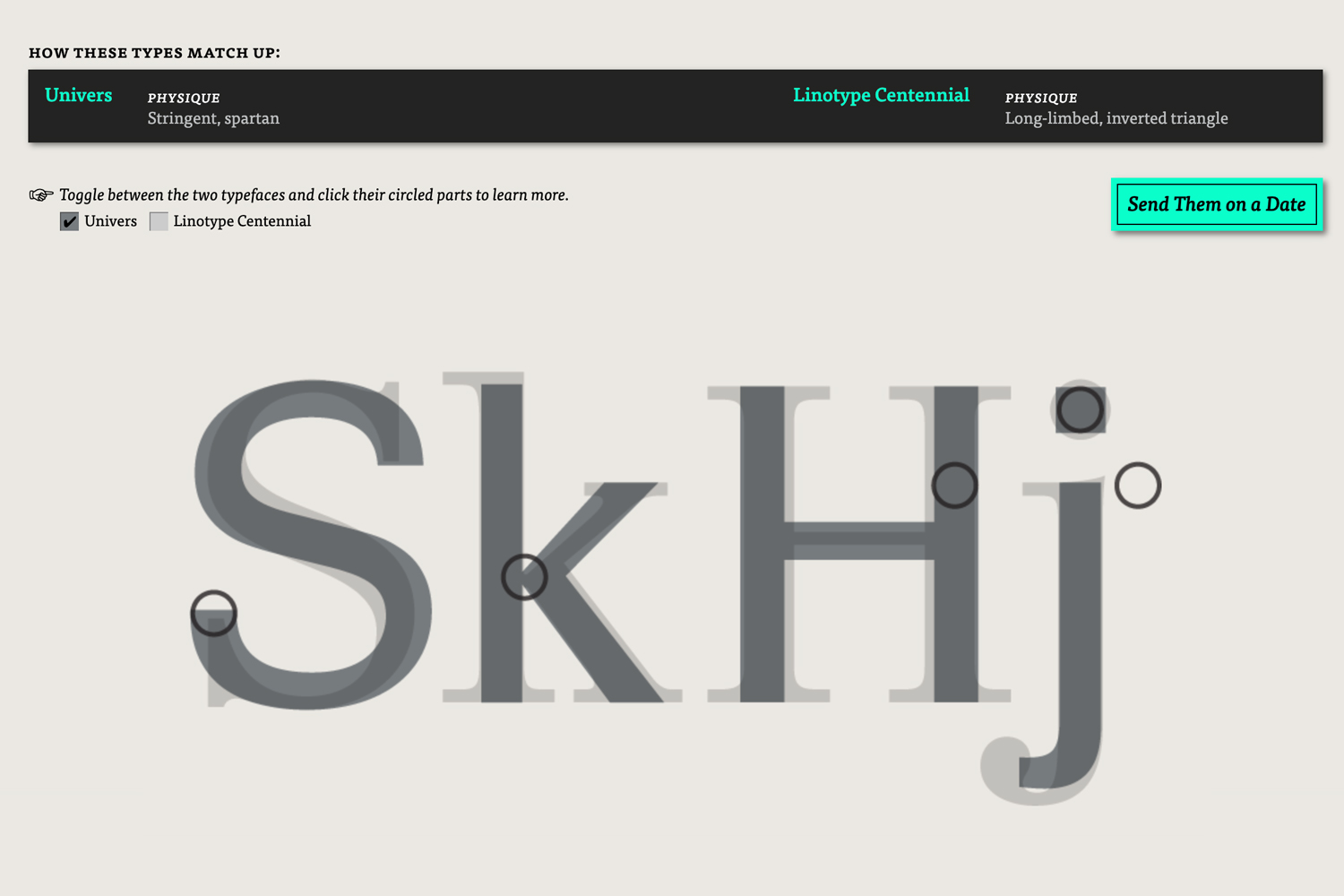
Type Connection es uno de los juegos que te ayuda a aprender a combinar tipografías. El mecanismo, inspirado en webs de cita, es muy ingenioso. Una vez decidida la tipografía que queremos emparejar, podemos escoger el criterio para la elección: la familia, algo similar, algo diferente o explorar el pasado. Elegimos uno de estos cuatro caminos y se nos ofrecen varias opciones tipográficas para combinar con la nuestra. A partir de aquí, obtenemos comparativas muy interesantes; entre ellas, datos históricos de las mismas y opciones de volver atrás si queremos probar otras opciones. Una buenísima opción esta web que ofrece grandes posibilidades de aprendizaje mediante un inteligente y divertido método lúdico. ¡Viva el amor tipográfico!
2. Acierta y vencerás
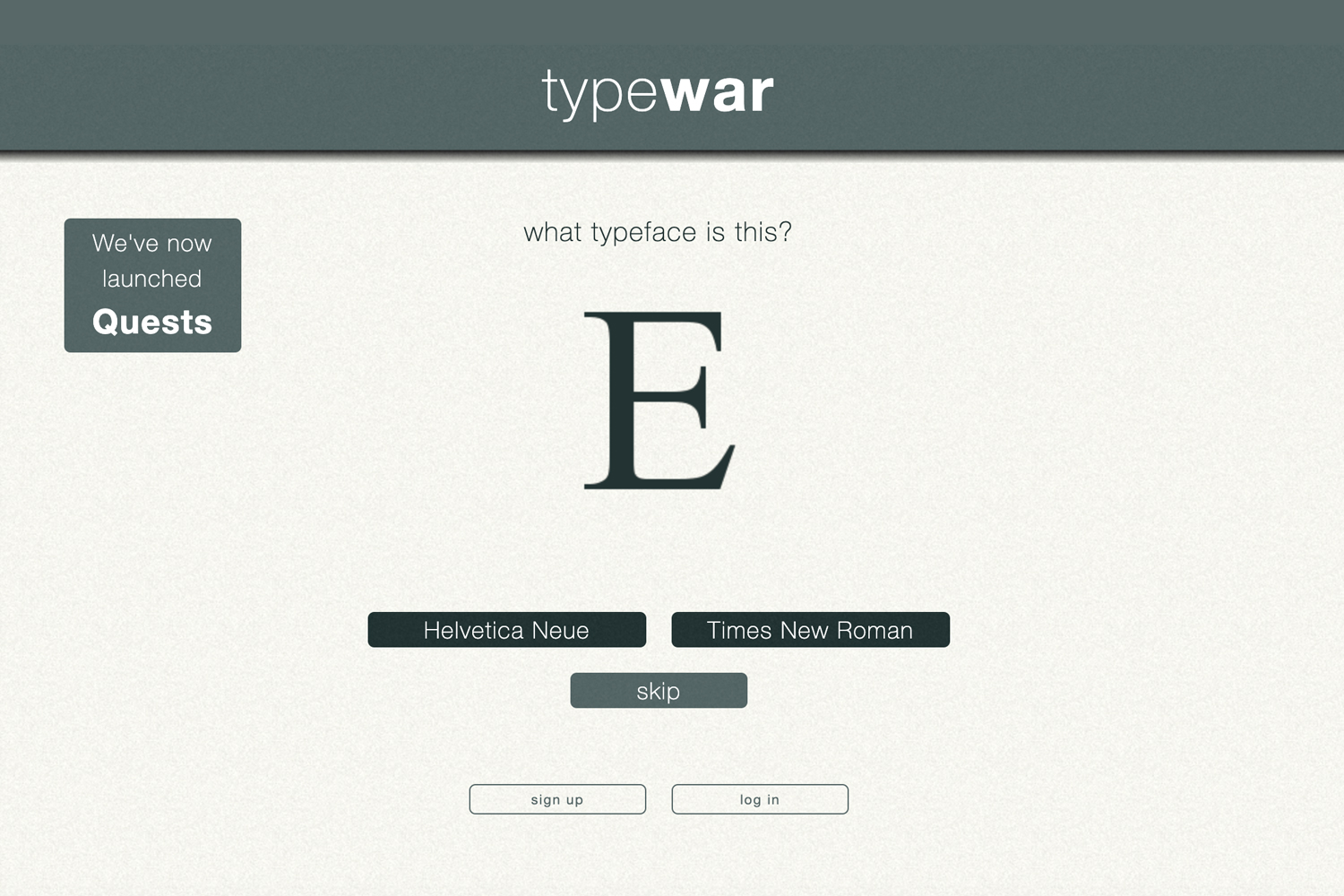
El mecanismo de Typewar es de los que enganchan. Se trata de acertar el tipo de letra entre dos opciones dadas. De este modo, a través de las puntuaciones que obtenemos, vamos avanzando en el juego. La pega es que requiere registro.
3. Dominar el arte del kerning
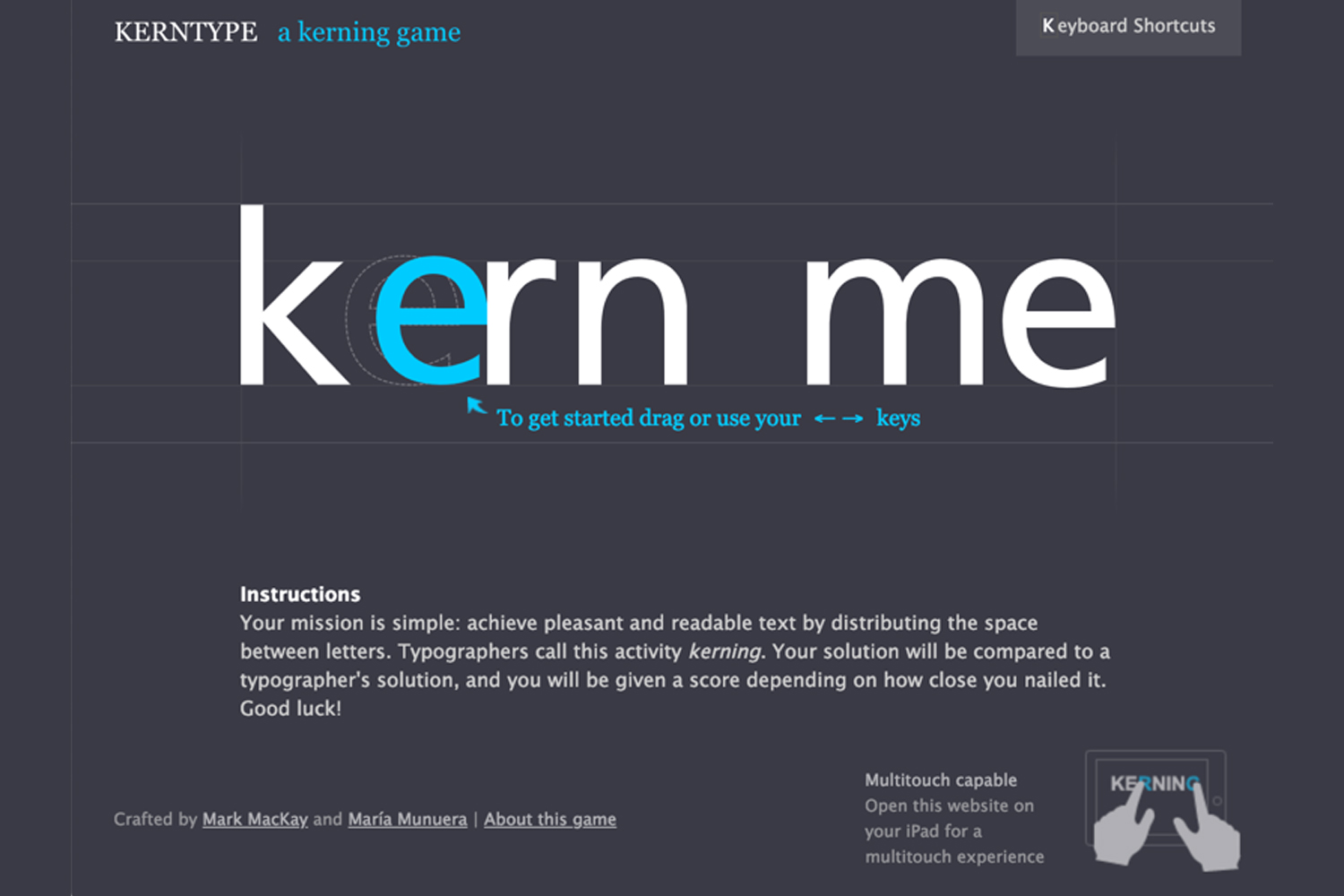
Method of Action es una elegante web con juegos muy bien planteados y desarrollados para practicar algunos rudimentos del diseño gráfico y la tipografía.
Uno de los juegos estrella es KernType, un juego para practicar el espaciado entre pares de letras, afinar la vista y entender que la tipografía y el espaciado tiene mucho que ver con los ajustes ópticos. Además de aprender a espaciar correctamente, lo hacemos con diferentes tipografías con las que nos podemos ir familiarizando.
4. Vienen curvas… de Bézier
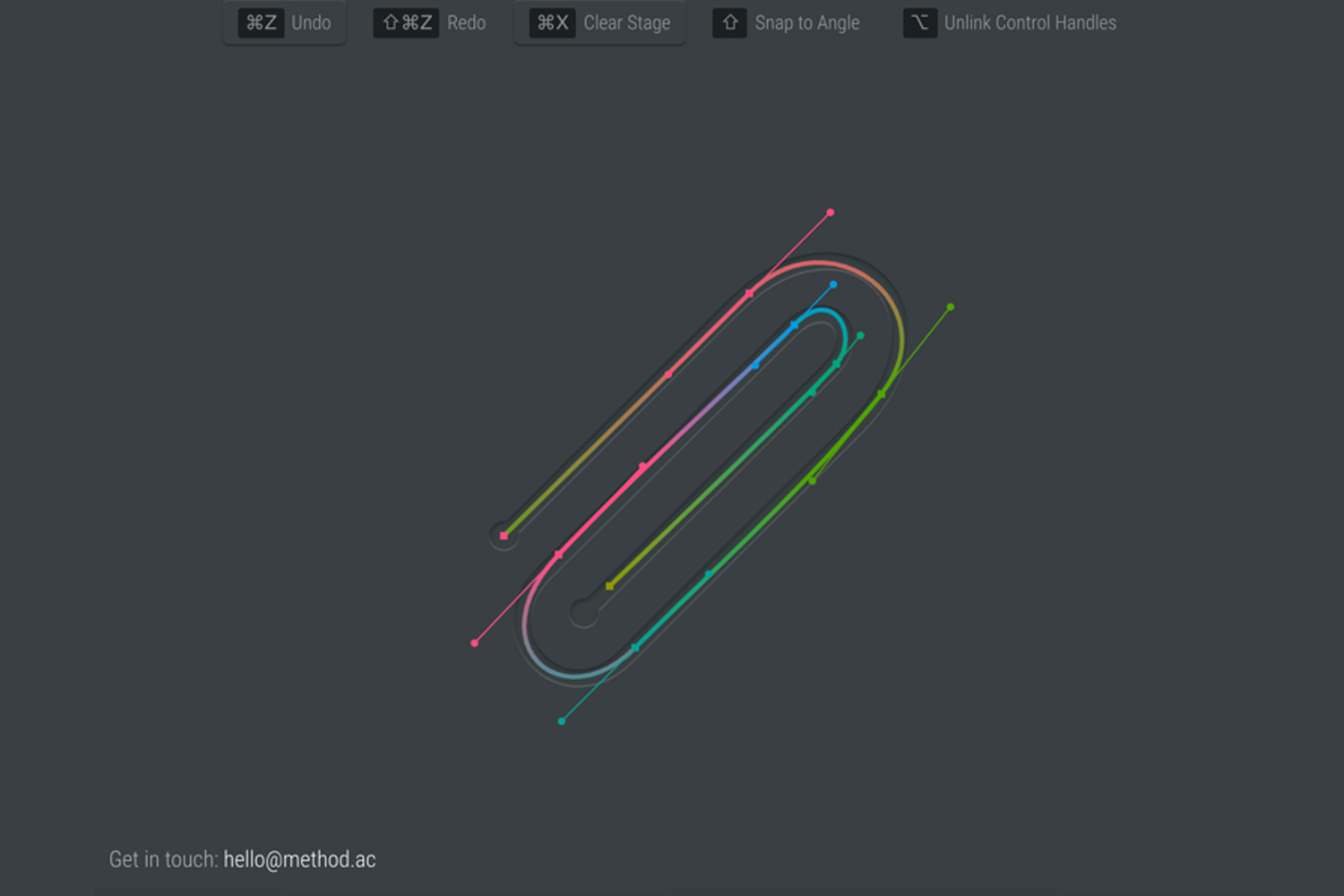
Dentro de Method of Action, también encontramos, The Bézier Game, un juego para iniciarse en el manejo de la famosa herramienta pluma, clave en el diseño vectorial ya sea tu finalidad ilustrar o crear una tipografía. El juego simula de manera simplificada el movimiento de la herramienta, los nodos, manejadores e incluso la «goma elástica» de Illustrator para previsualizar el trazado entre el primer punto de ancla y el puntero del ratón. Un juego de lo más útil.
5. Afina el ojo tipográfico
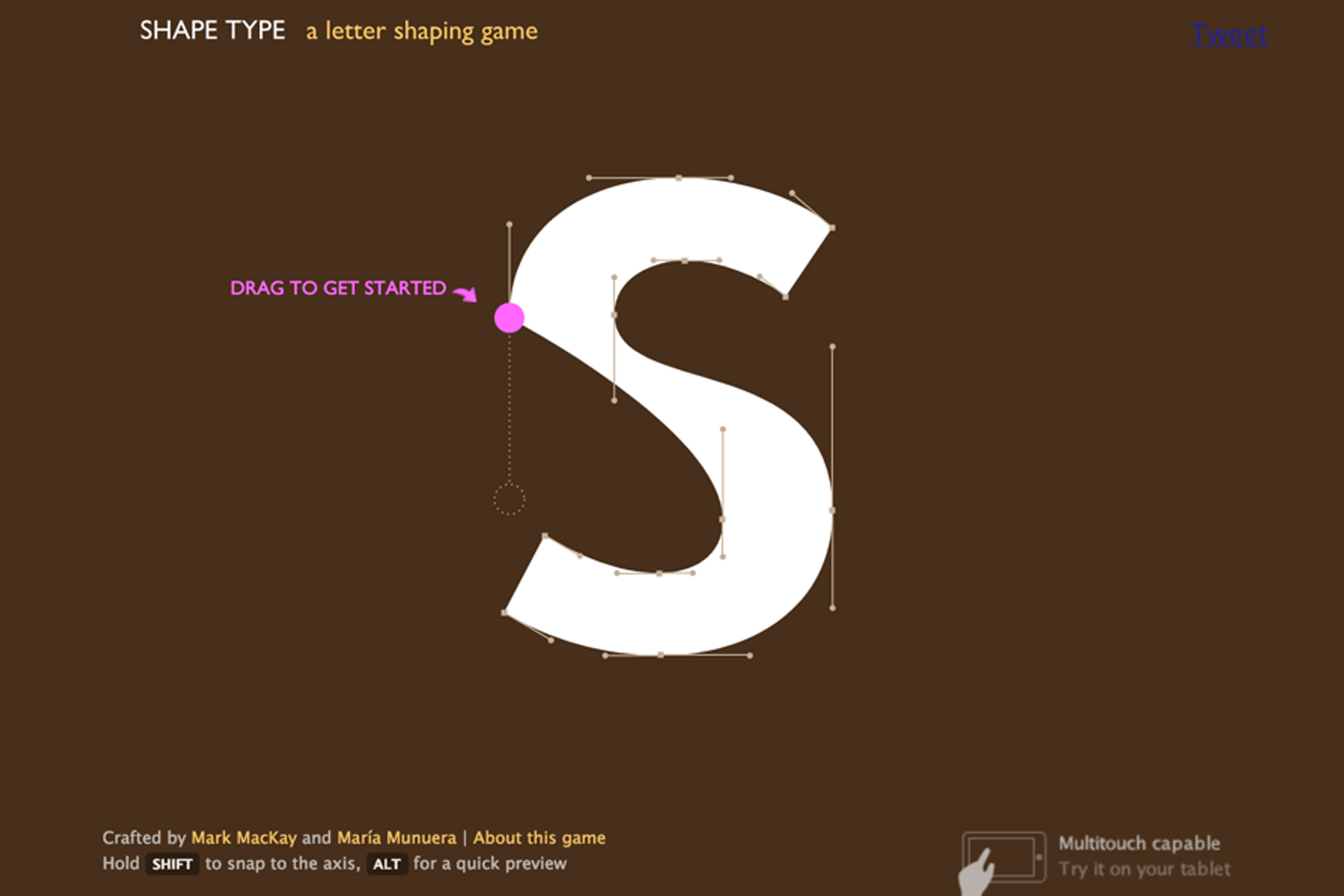
El tercer juego tipográfico de Method of Action es Shape Type, un imprescindible para afinar curvas y con ello perfeccionar las formas de las letras y sus contraformas, que son igual o más importantes. Como podrás comprobar, esta suite es lúdica, muy distraída y con mucho sentido práctico.
6. Encuentra las diferencias, si puedes
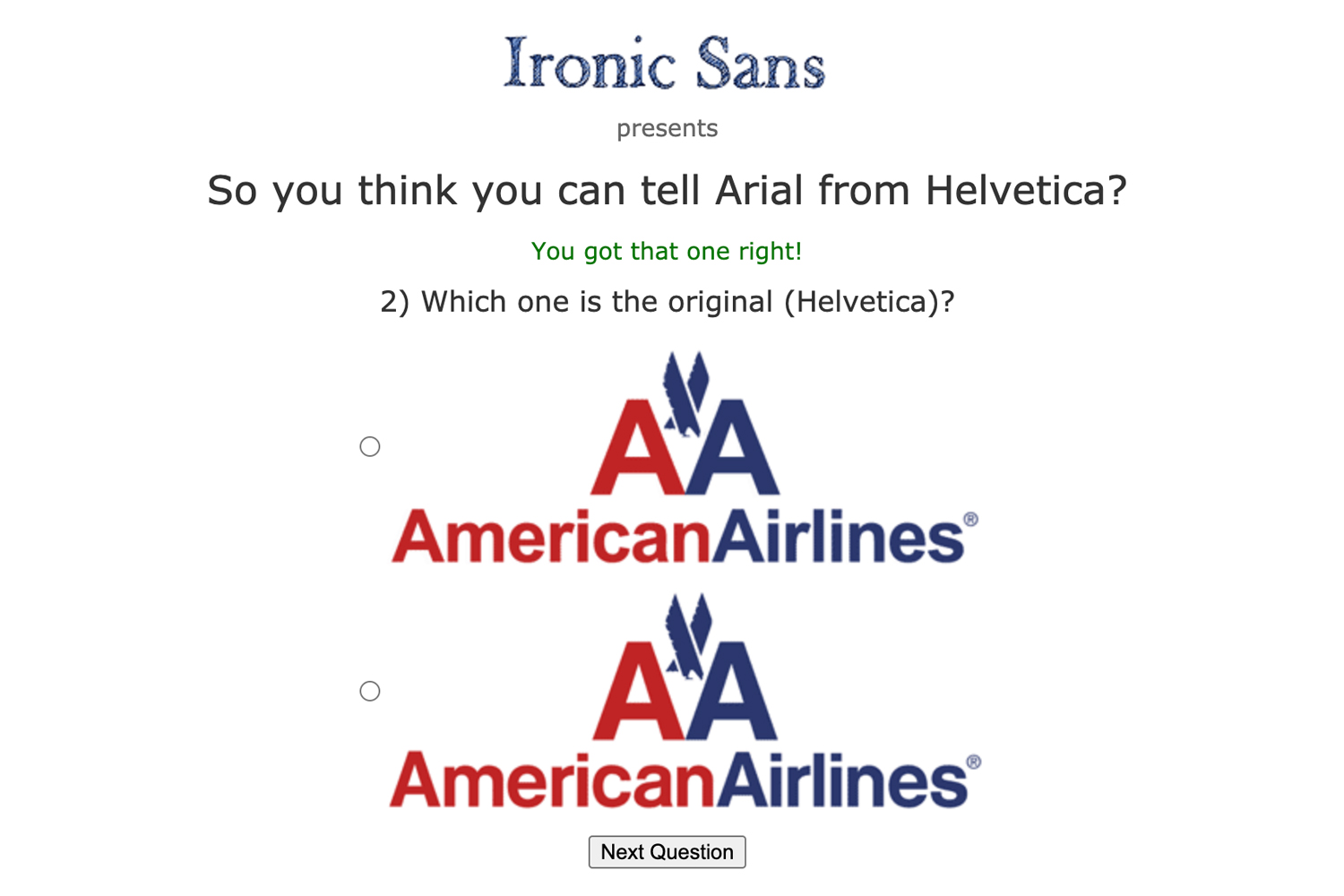
Por último, os proponemos un juego con mucho de esa clase de sentido del humor puñetero y afilado, muy anglosajón. Se trata de Helvarialquiz, donde se plantea la siguiente pregunta: ¿Crees que puedes distinguir entre Arial y Helvetica? Y como podrás comprobar, no es tan fácil distinguirlas.
7. Apunta y dispara
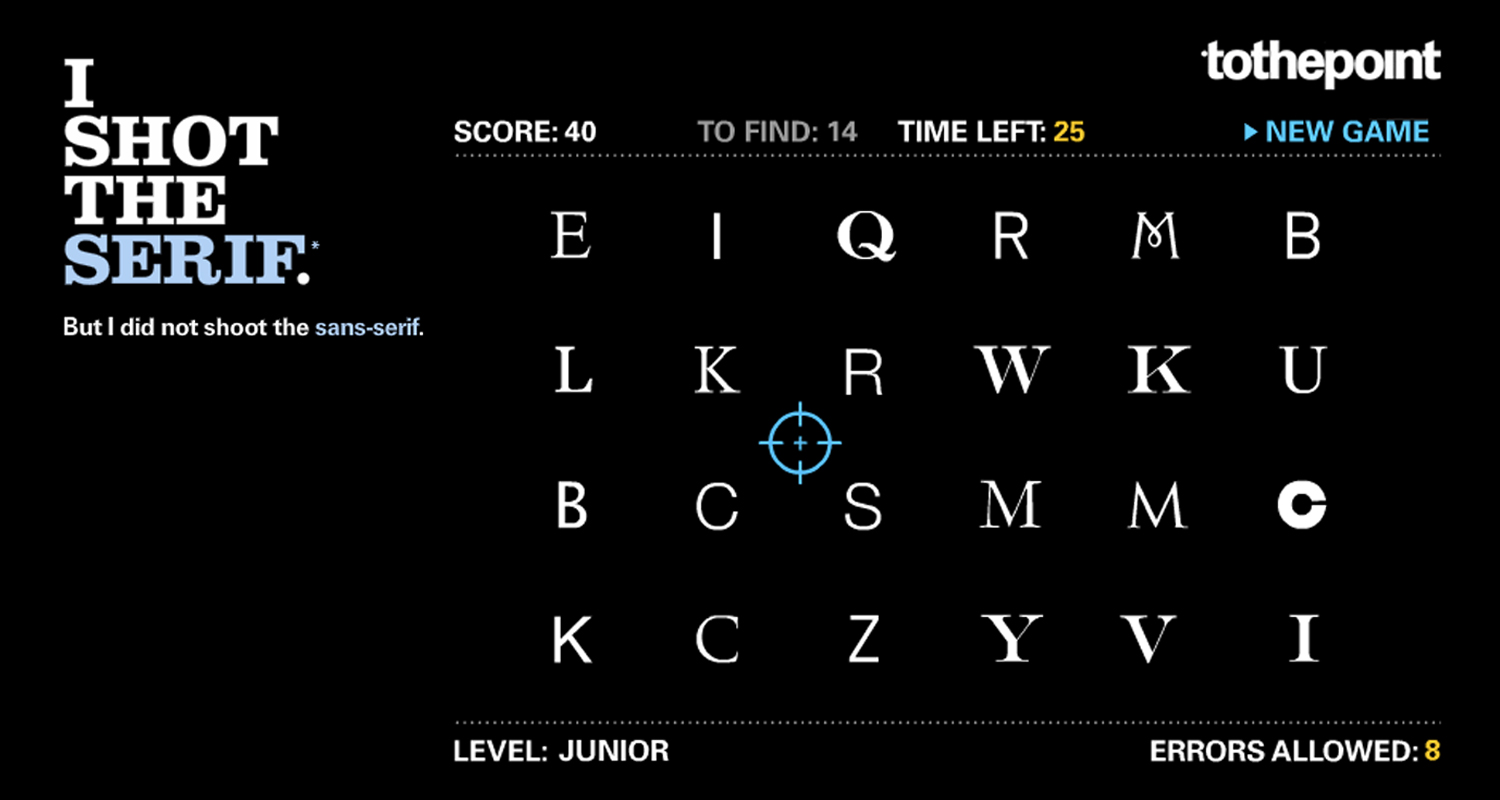
En I shot the serif tu cometido es disparar todas las fuentes con serifa de la pantalla en un cierto tiempo. Puedes elegir diferentes niveles y oye, engancha. No es tan fácil como parece y se agudiza la vista y el reconocimiento de tipografías serif. Recomiendo jugar desde el móvil, tiene una app disponible para iOS. Un juego para gente rápida.